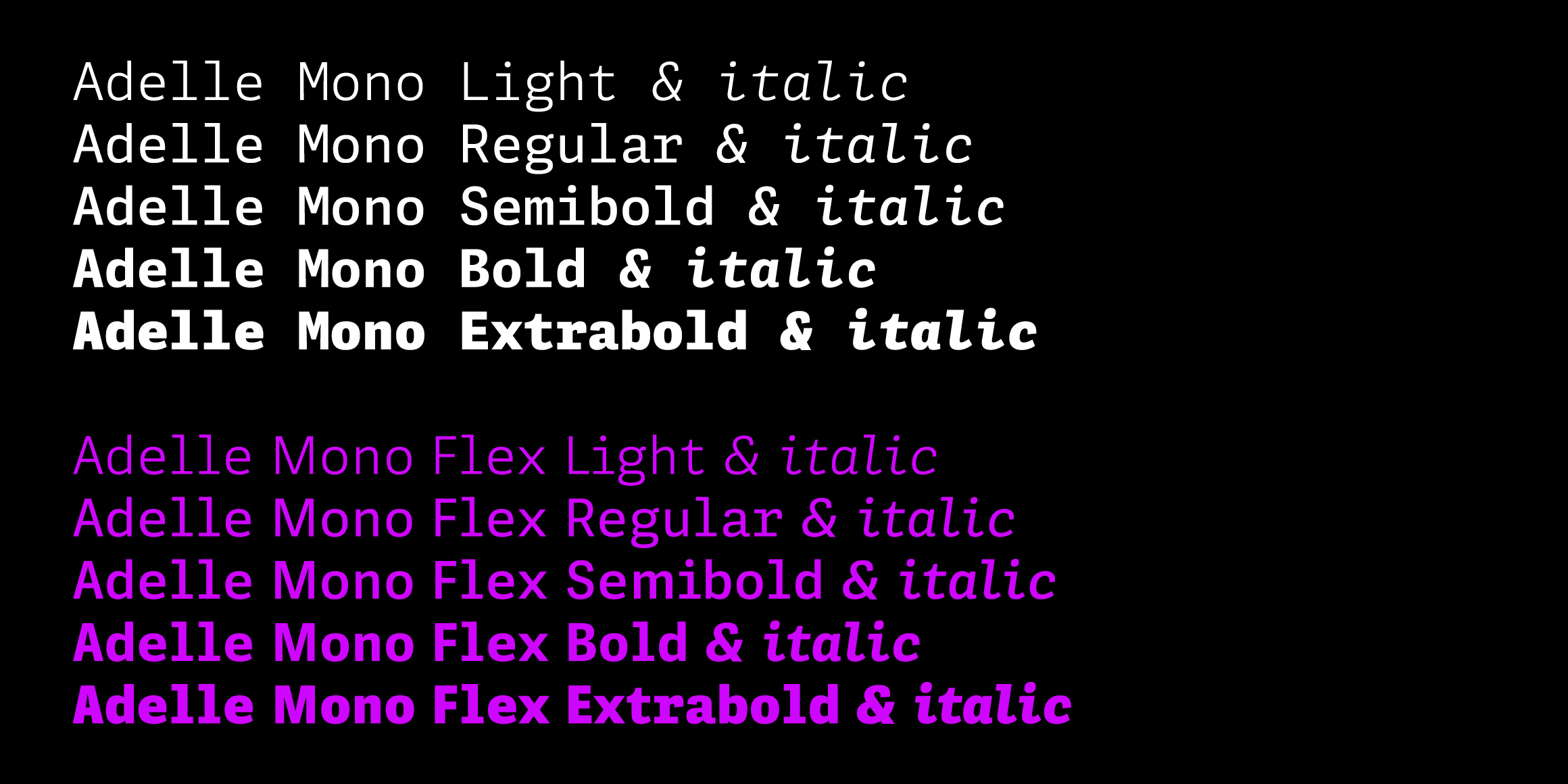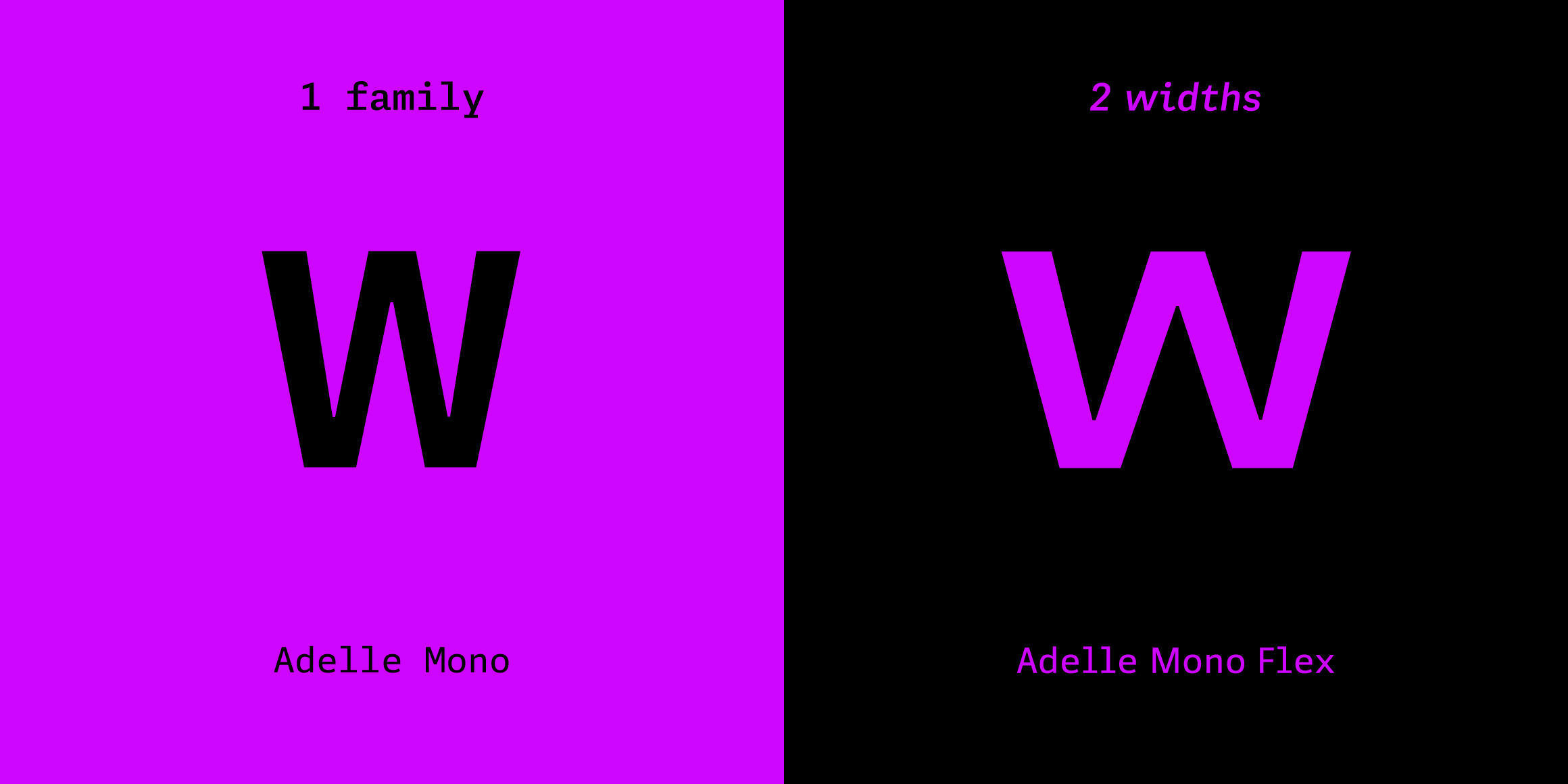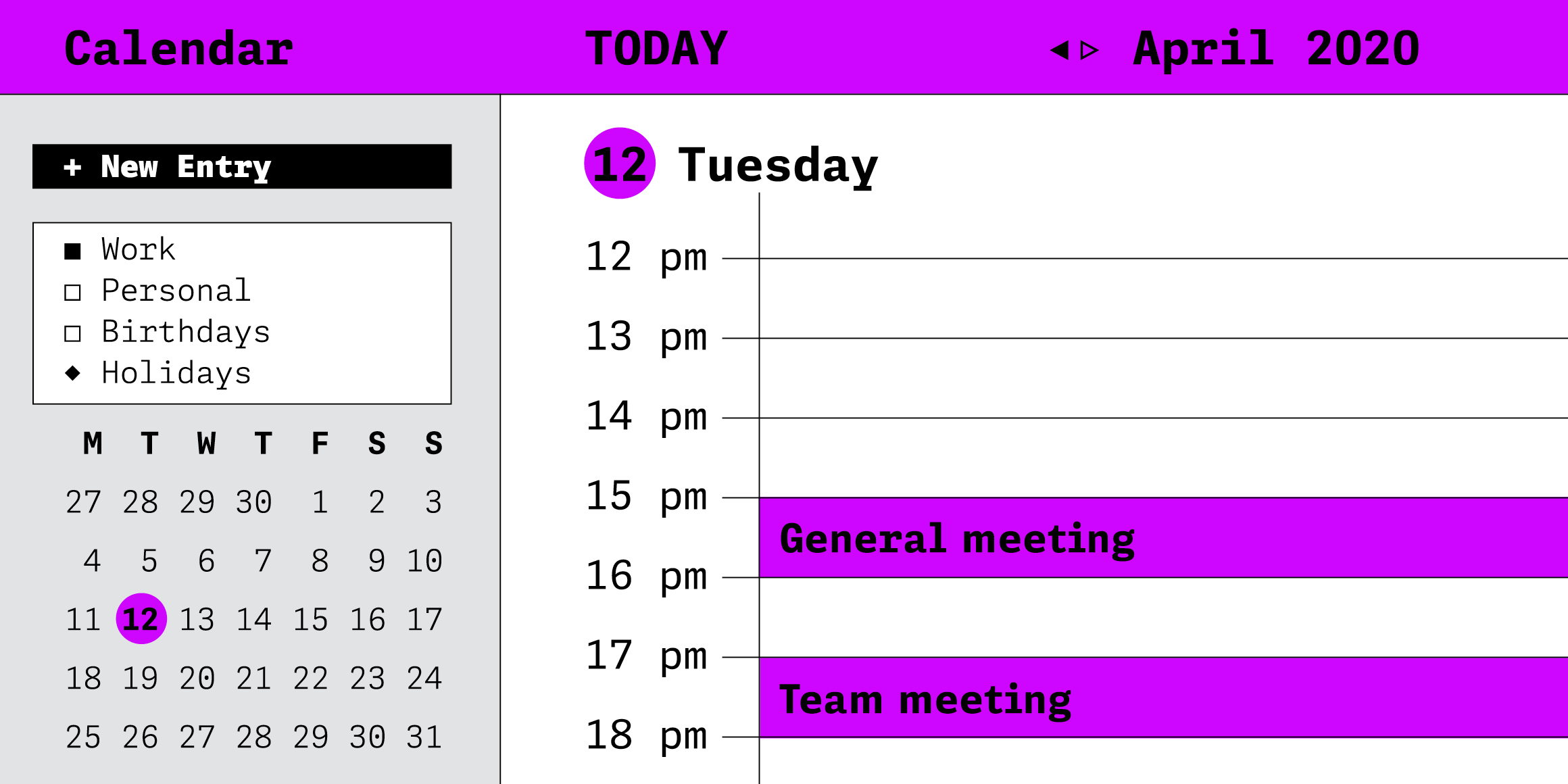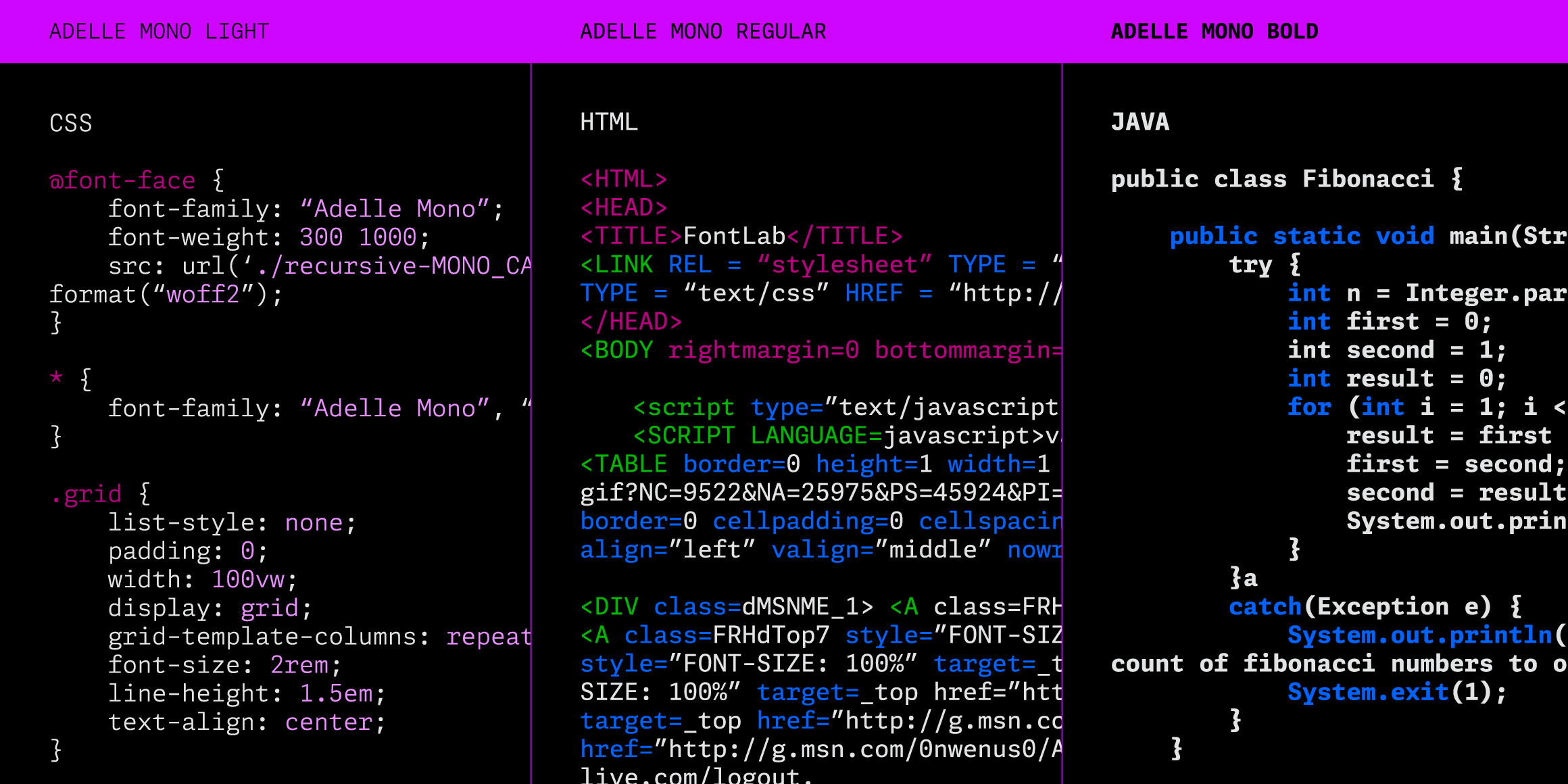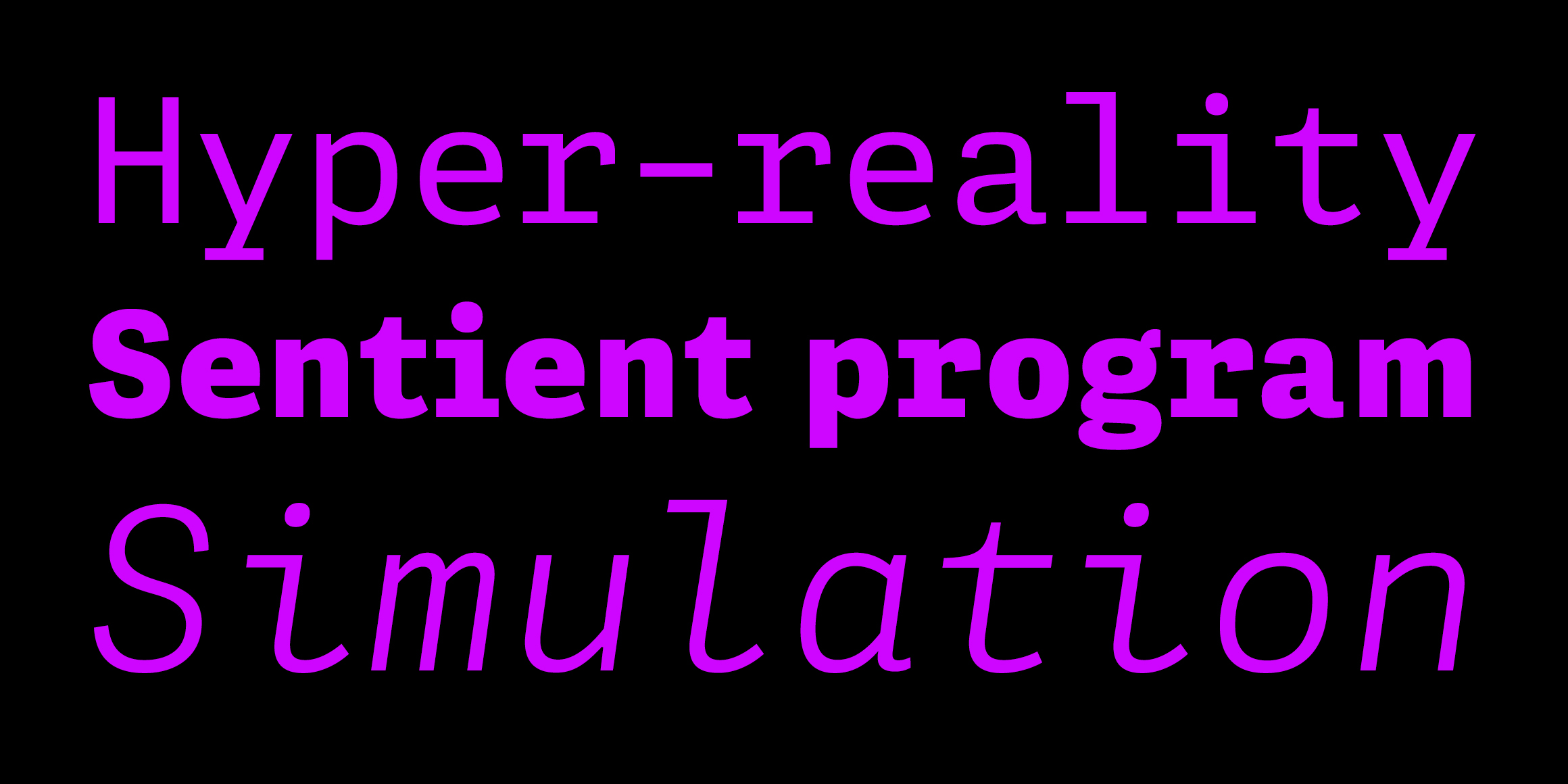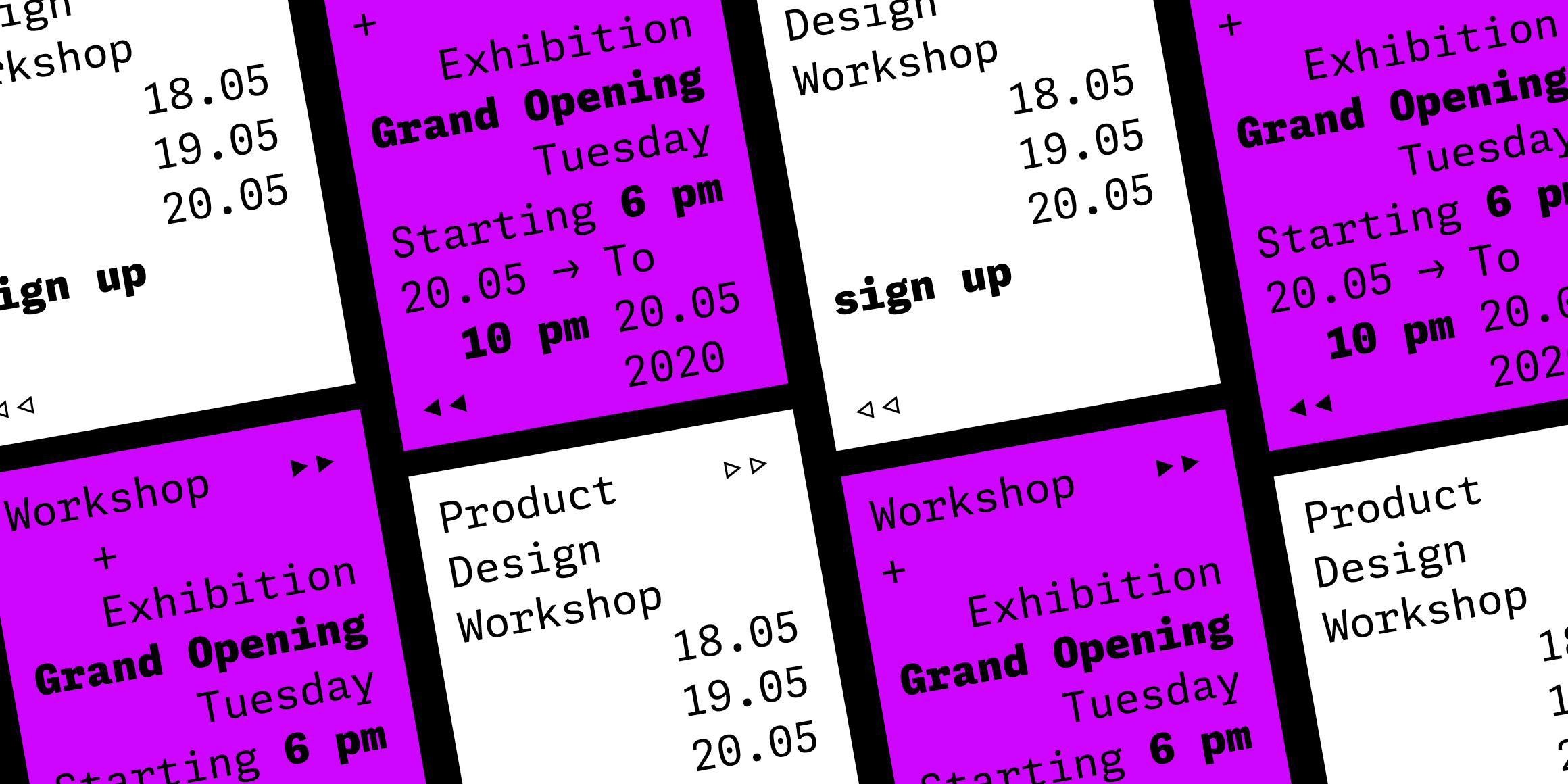
Adelle Mono
Adelle 패밀리는 스타일을 계속 확장하여 Adelle Mono 및 Adelle Mono Flex를 출시했습니다. Adelle Mono는 고정폭 서체로 개발자와 프로그래머들이 코딩 등의 실무에 사용하기 편리하며, 디자이너 또한 라틴 고정폭 서체가 가지는 특유의 미감을 디자인 요소로 활용하기 좋습니다. 하지만 고정폭이기 때문에 보다 세밀한 디자인을 위해 사용할 때 불편함이 발생하기도 합니다. 이를 보완하기 위해 Adelle Mono 패밀리는 고정폭과 동일한 디자인 콘셉트를 가지는 비례폭 서체 Adelle Mono Flex를 포함합니다. 더불어 함께 제공되는 Mono Upright와 Italic 2종의 베리어블 폰트로 사용자가 필요한 굵기의 폰트를 선택해서 사용할 수 있습니다. 개발자와 디자이너를 모두를 고려하여 세심하게 디자인 된 20가지 스타일인 Adelle Mono를 필요에 따라 알맞게 사용해서, 각 상황에 맞는 최적의 결과물 만들어보세요!